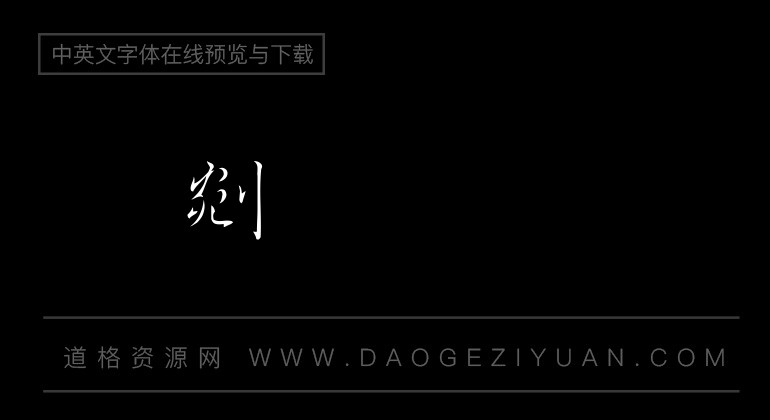
金梅毛草行体是一款由金梅字体工作室设计的简洁清新易读的行楷书体字体,是毛笔行书的改良版,由古韵行楷书演变而来,具有稳重、清新、大气的特点。金梅毛草行体字体的特点是笔画粗细均匀,结构紧凑,笔画流畅,毛笔字的特点得到了良好的保留,使得字体更加精致、清新,能够满足不同的设计需求。文件名:JinMeiMaoCaoXingTi-1.ttf
金梅毛草行体是一款非常不错的手写艺术字体,具有很好的视觉感,适合于文化类的宣传设计、商业类品牌的广告和产品包装设计以及个性化文字排版等较多场景。